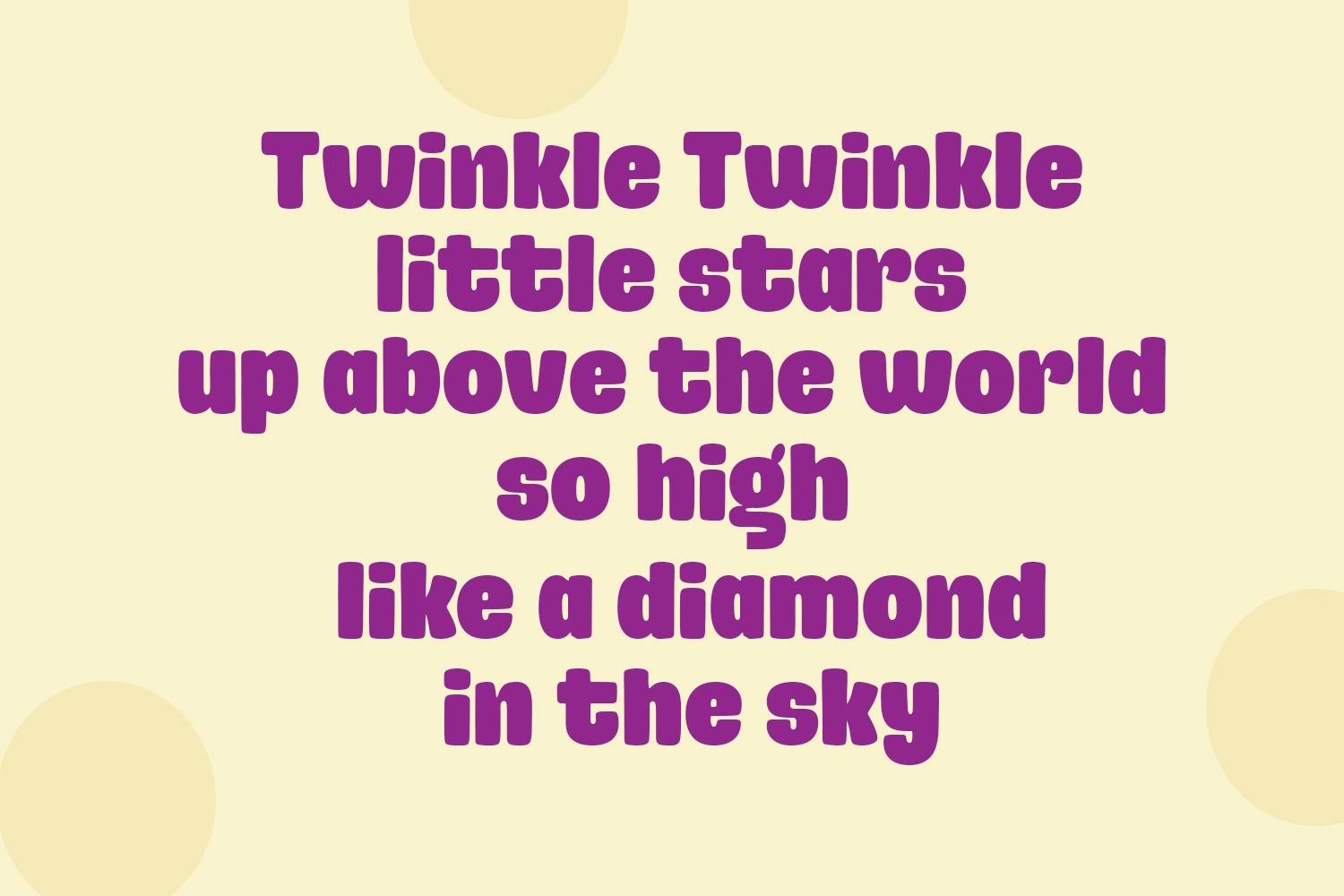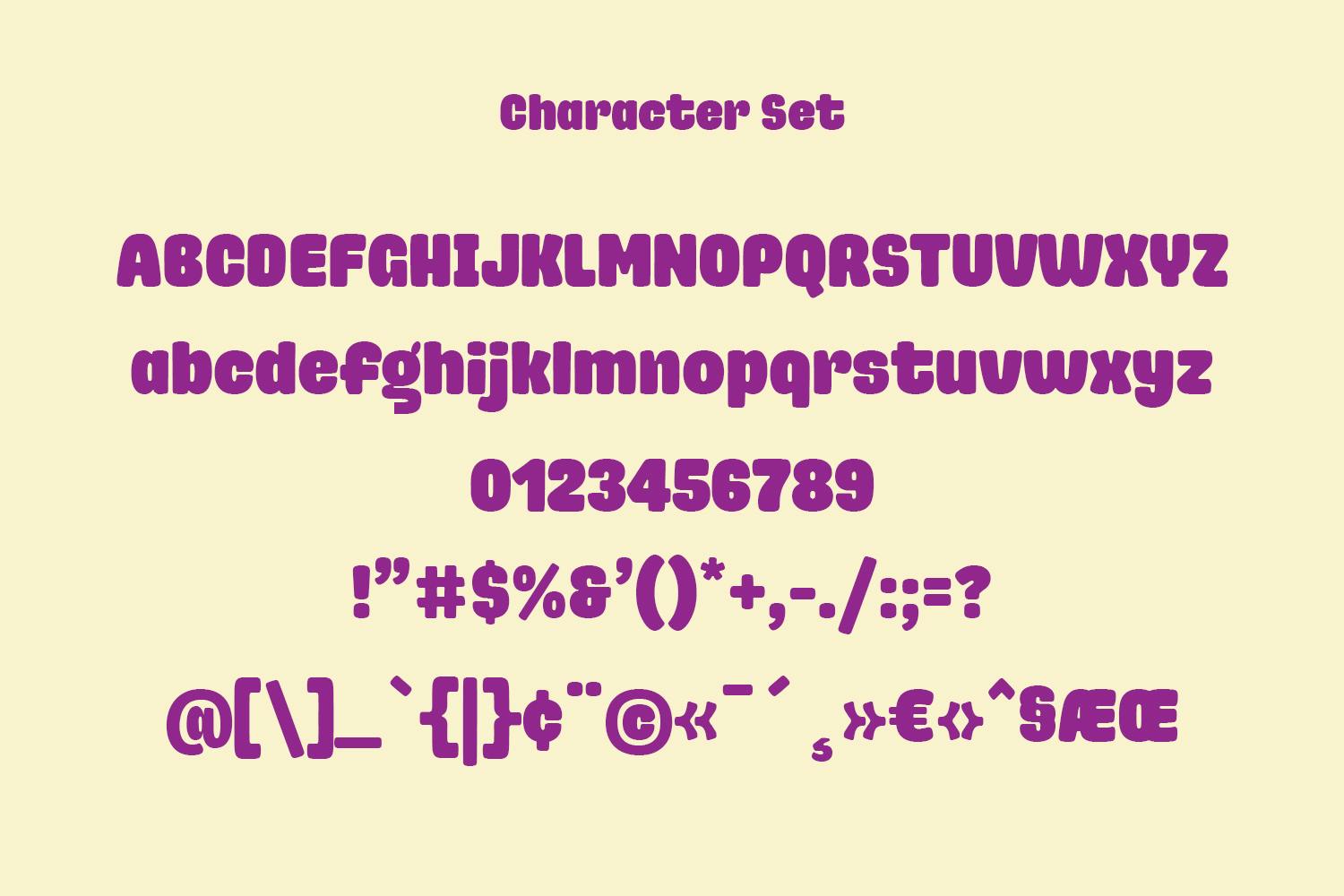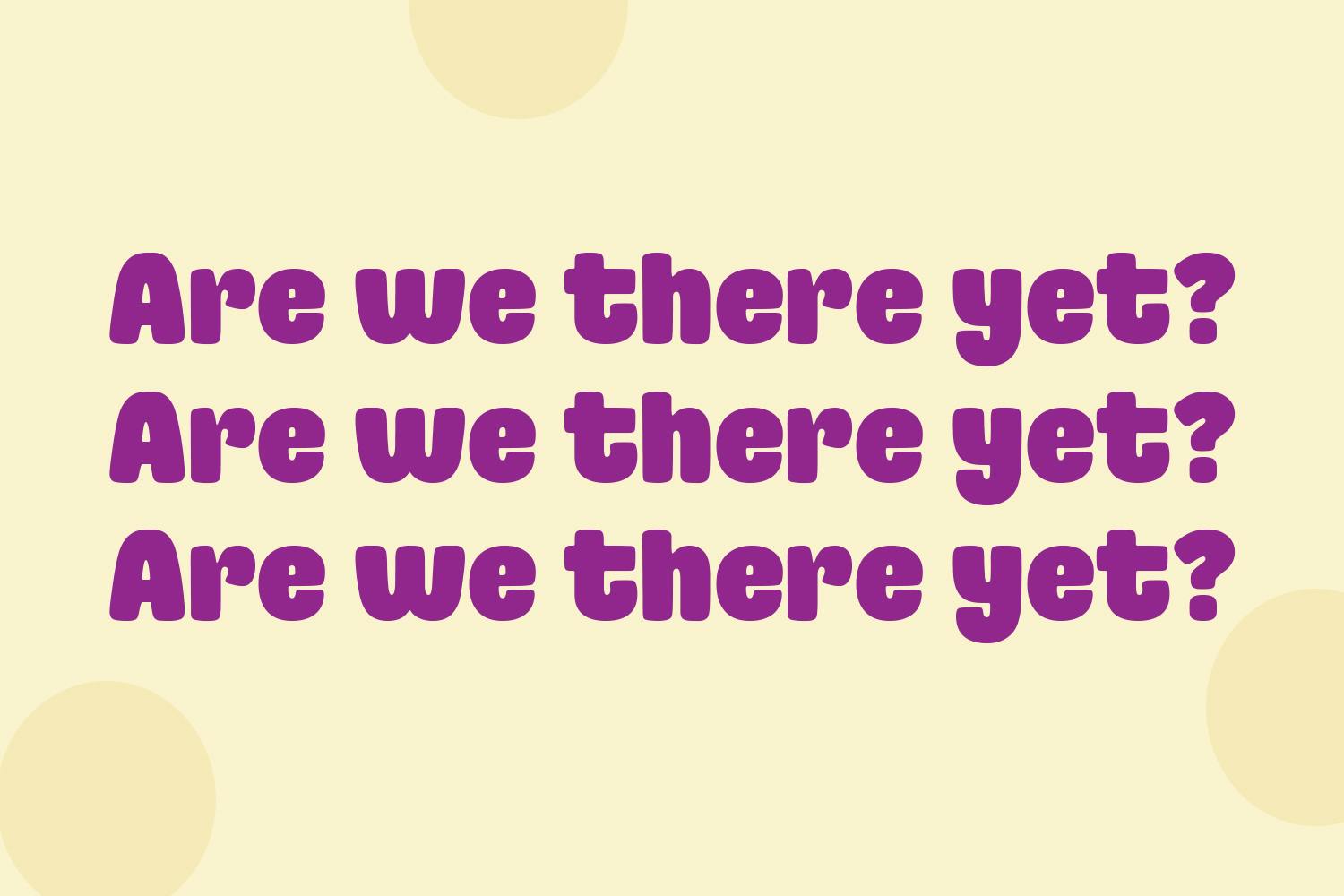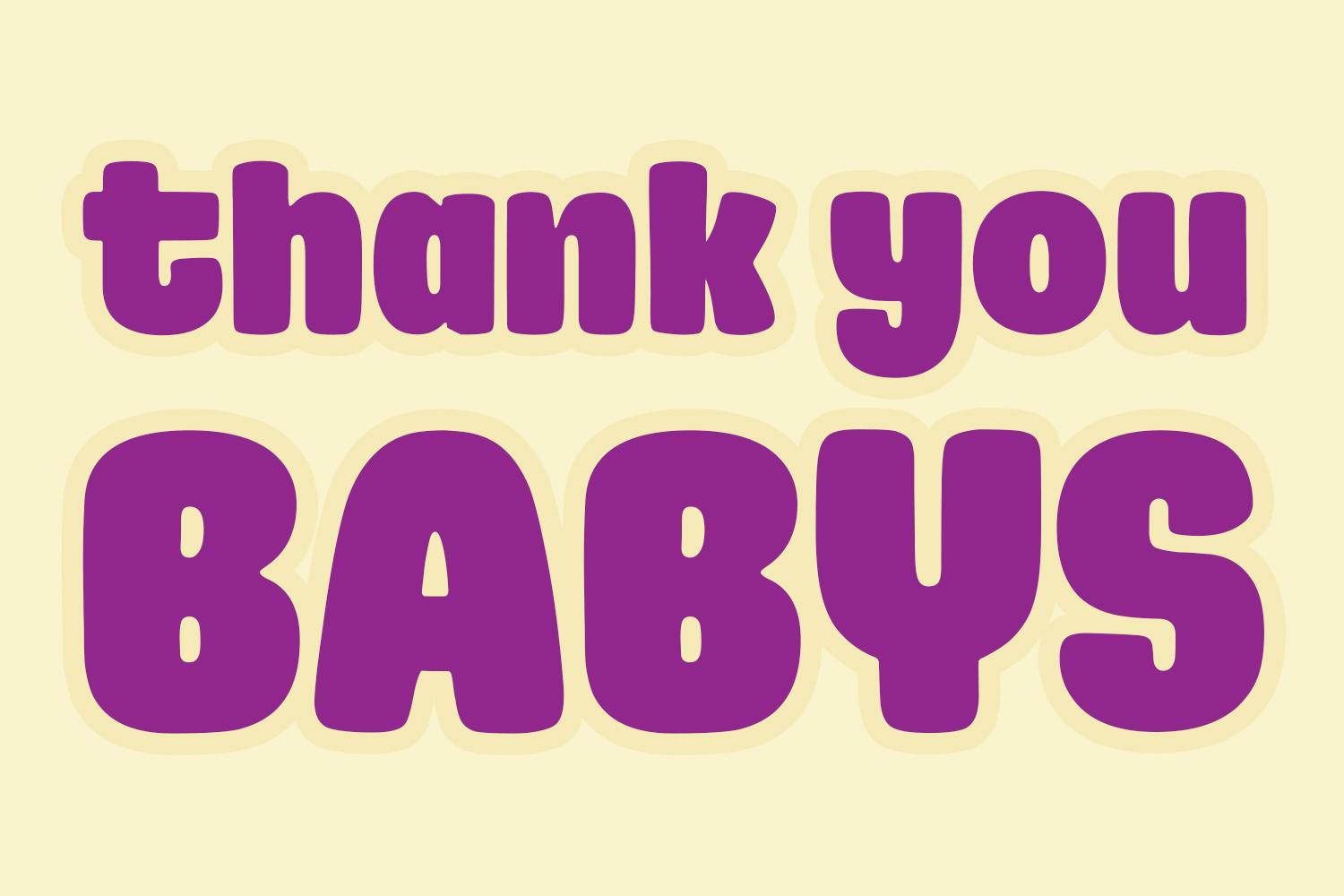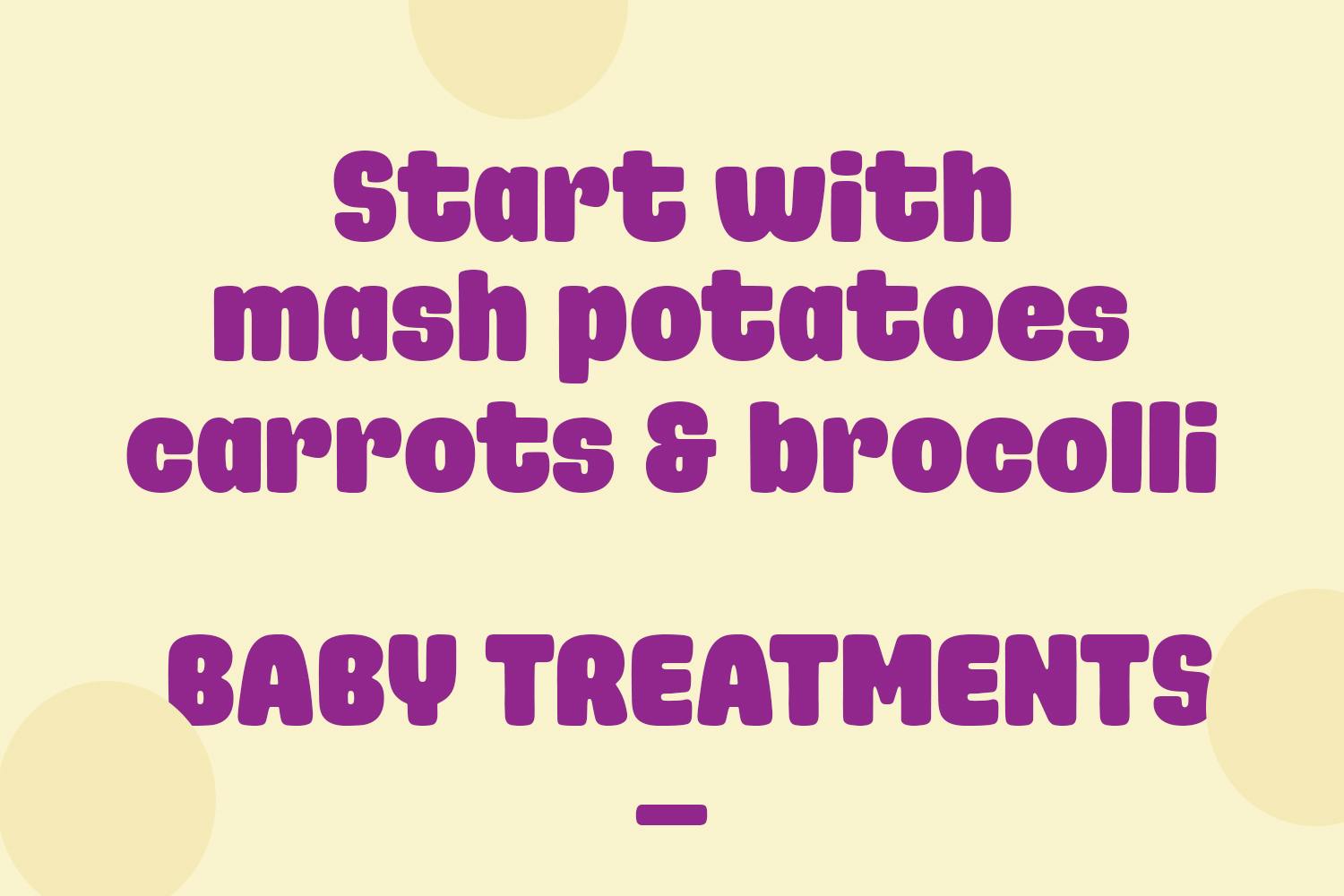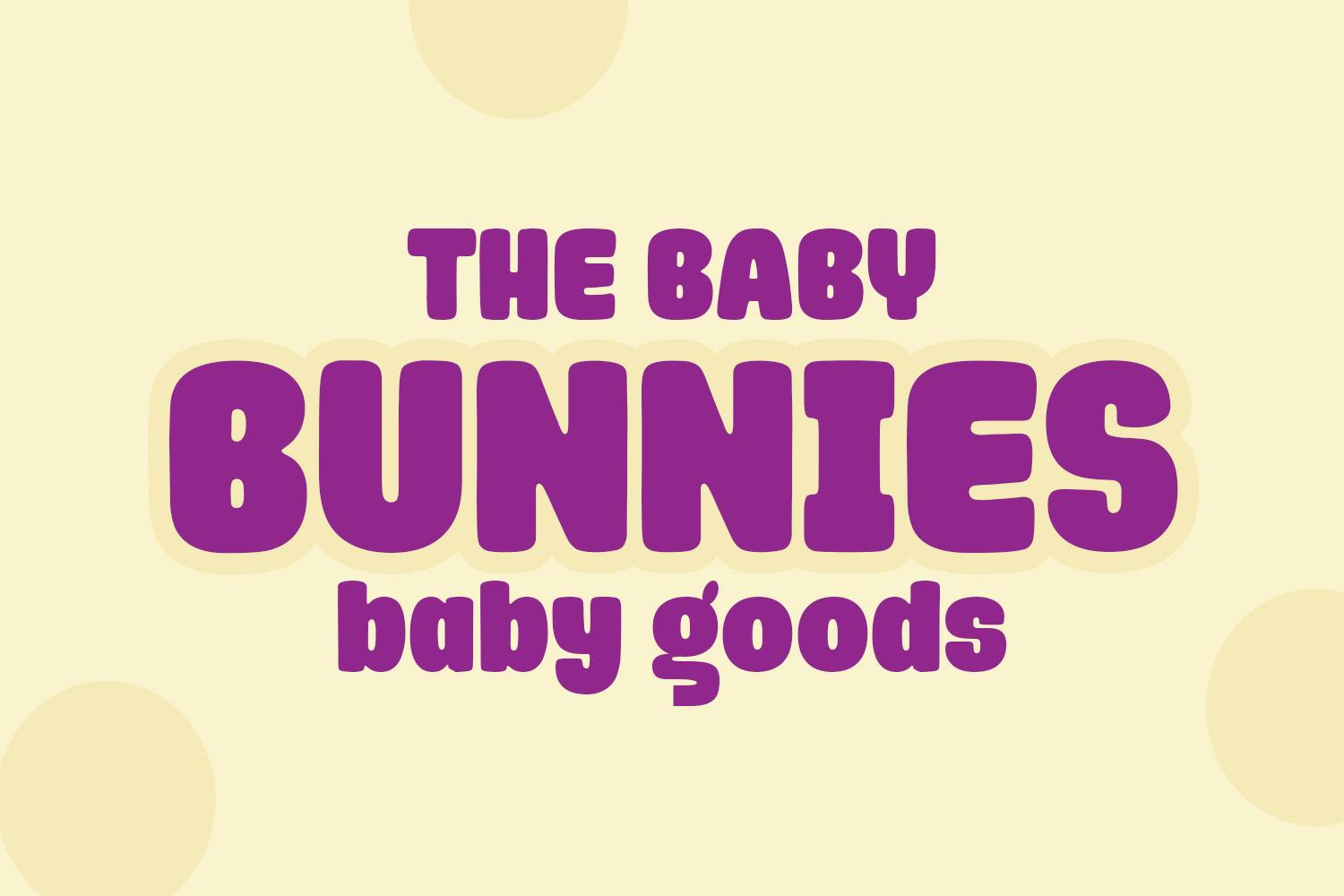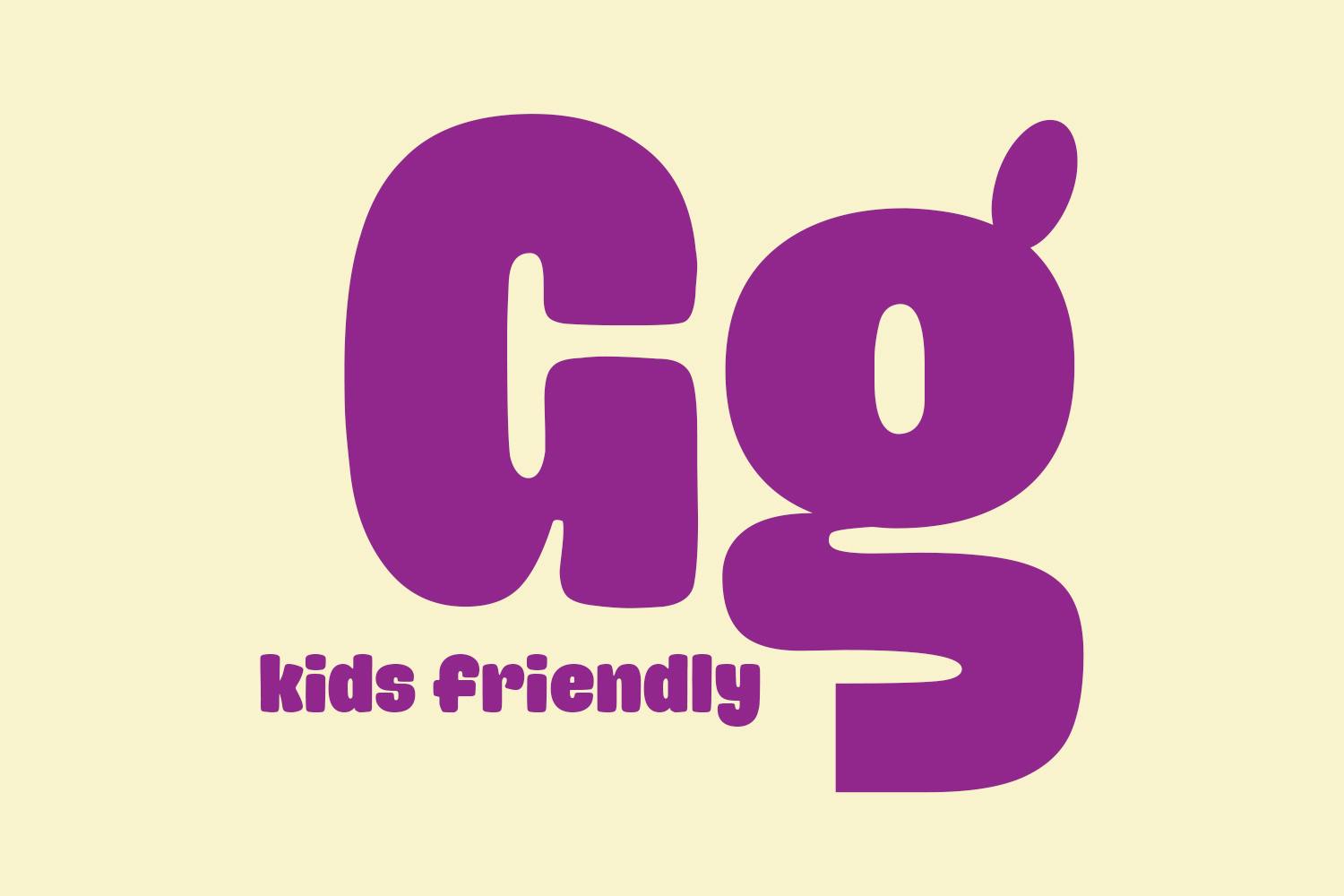
Kloges یک فونت دستنویس و غیررسمی است که با طراحی bold و کاراکترهای جذاب همراه با برخی لیگاتورها و جایگزینها به شما کمک میکند تا آثار خلاقانهتری خلق کنید. این فونت از بیش از 100 زبان مختلف پشتیبانی میکند و برای طراحی لوگو، شبکههای اجتماعی، عناوین فیلم، عناوین کتاب، متنهای کوتاه و حتی نامههای طولانی مناسب است. فونت Kloges انتخابی عالی برای متنهای ثانویه شما با فونتهای sans یا serif خواهد بود. با استفاده از فونت Kloges، آثار شگفتانگیزی خلق کنید.